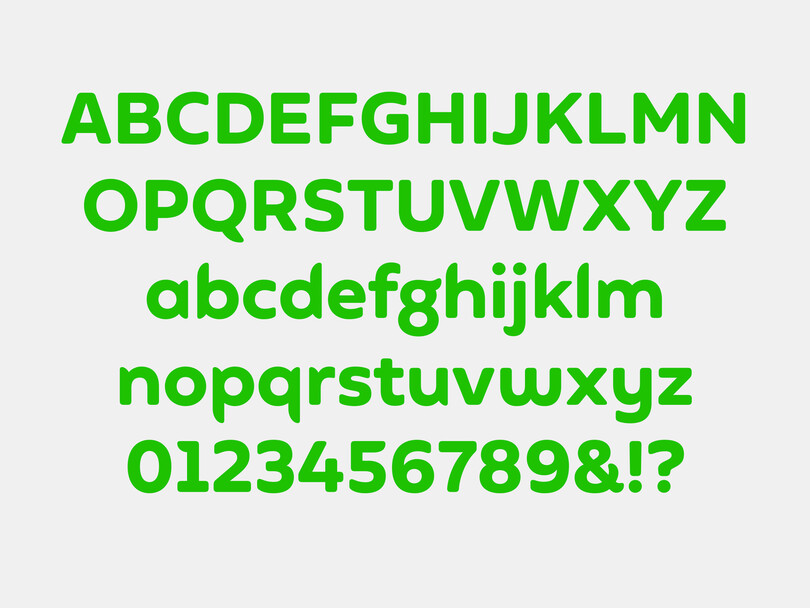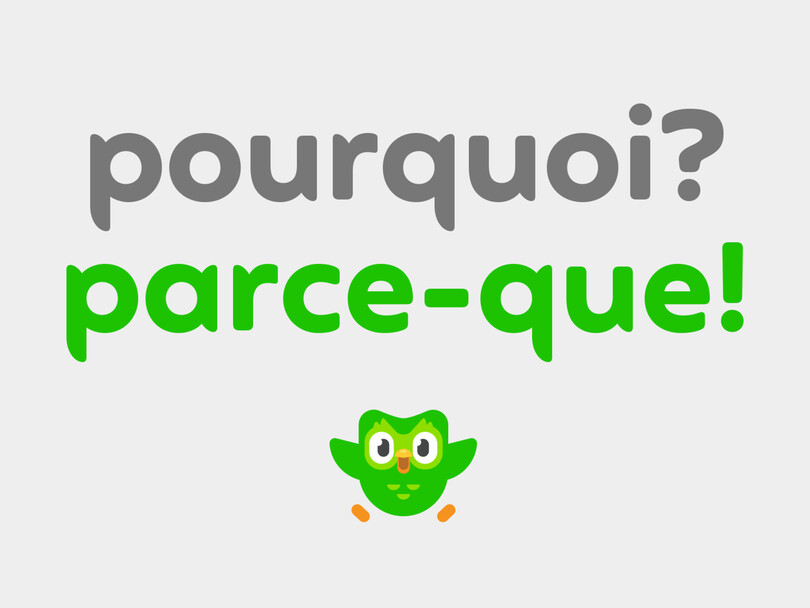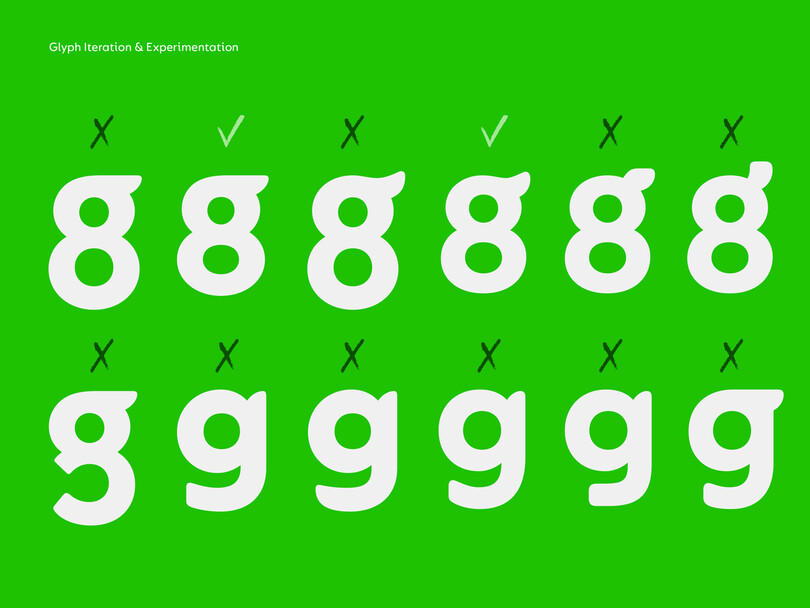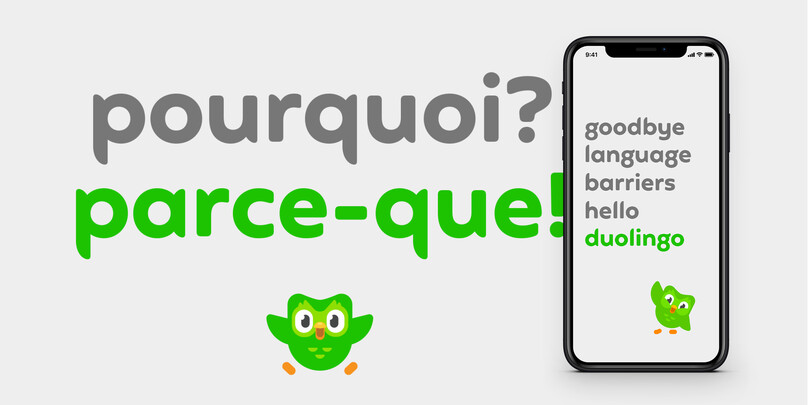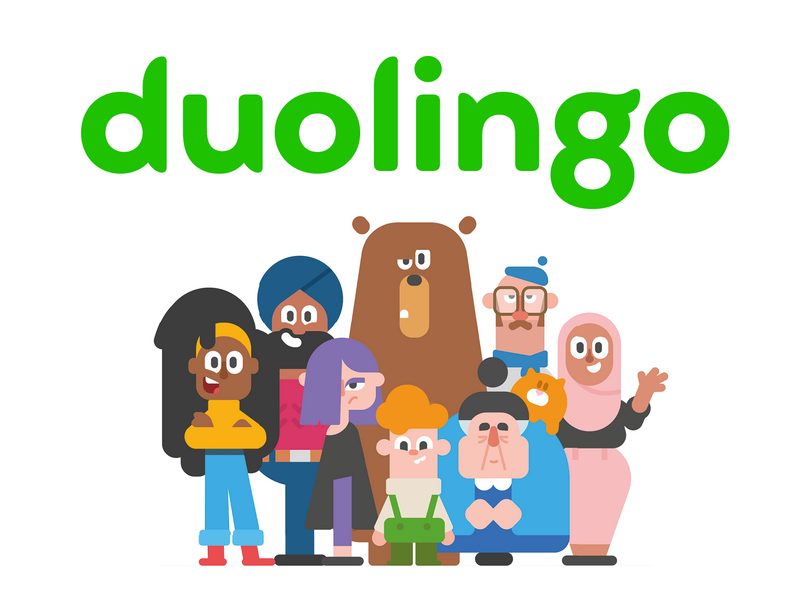
言語学習アプリDuolingoのためのカスタムフォント
「 カスタムフォントは、ブランドの再構築においてもっとも重要な要素の一部です。企業にとって良いブランドフォントとは、企業のためのブランドの声として機能するように精巧に設計されていることです。 」
Phil Garnham(フィル・ガーナム)シニア・クリエイティブ・タイプディレクター
Duolingoは、3億人以上のユーザーが利用する人気の言語学習ウェブアプリです。英語だけでなく韓国語や中国語などさまざまな言語を学ぶことができます。グローバルで展開するサービスの顧客に向けて、世界で統一したブランドの声を届けるため、Duolingoはリブランドを検討しプロジェクトがスタートしました。
ロンドンに拠点を置くブランドコンサルタントのジョンソン・バンクス(Johnson Banks)を通してマスターロゴとカスタムフォントの依頼を受けました。
まずは、「デュオ」というDuolingoの象徴的なフクロウのマスコットからインスピレーションを得て、マスコットのデザインに内在する形状が書体デザインにどのように影響を与えているかを調べ始めました。そして、フクロウの翼の形状とれに込められている想いを文字の形に取り入れる方法を考えていきました。
新しいロゴを制作するためのプロセスと初期バージョンのロゴを共有し、方向性をしっかりと把握できるようにしました。翼の形状からディテールを追求し、さまざまな太さや丸みの度合いを試し、慎重に調整しました。
「g」の形状はロゴデザインに不可欠であり、書体全体の雰囲気にも重要な要素であったため、様々なアプローチが検討されました。
ロゴが決定すると、そのロゴのデザインを軸に見出しフォントの方向性を決めて、主要な単語やフレーズに拡張していきました。文字の形がブランドの声として機能するかどうかを初期の段階から入念に検証しながら進めることによって、よりクリエイティブなアイデアが生まれ、スムーズに決定していくことができました。
マスターロゴが様々な検証を経て完成した後、書体の開発に着手しました。デジタルプラットフォーム上のテキストとして、フォントの比率を微調整することでロゴの個性を均等になるよう調整しました。また、いくつかのデザインから選べる代替文字を制作するため、声のトーンとサンプルメッセージを何度も徹底的にテストしました。
フォントに大文字が必要かどうかについて議論があり、小文字のように翼の形状を模した大文字も検討しました。テストの結果、セリフつきの翼は統一感のないアルファベットを作り出し、すべて大文字の組版は想定より強すぎる印象となってしまうと感じました。また、ドイツ語などの大文字を頻繁に使用する言語にも配慮しました。最終的に、シンプルな形状を選び、大文字が小文字を際立たせる役割を果たすデザインを採用することにしました。
技術的なニーズに合わせてデザインを調整し、フォント内でマスターロゴを入力可能な文字として組み込み、任意のキーボード設定で簡単にアクセスできるように代替文字をプログラムしました。
企業のアイデンティティである、マスコットの雰囲気を持った書体をデザインするというところからスタートし、唯一無二のユニークなカスタム書体、Feather(フェザー)が誕生しました。
企業にとって良いブランドフォントとは、企業のためのブランドの声として機能するように精巧に設計されていることです。Duolingoの場合、「g」は非常に特徴的なデザインとして制作しましたが、すべての文字とも調和し、単語から注意をそらすほど強くにならないように配慮しました。形(個性)と機能(デジタルヘッドライン)のバランスをとり、顧客にとって非常に使いやすく、読みやすい、また同時に独自性を持っているDuolingoとして認識できるフォントを制作しました。
Feather はすでにブランドの重要な一部となり、Duolingoのブランドコミュニケーションのすべての側面に展開されています。また、Duolingoのデザインチームとマーケティングチームと共同で行ったブランドの全面刷新と並行して行われています。